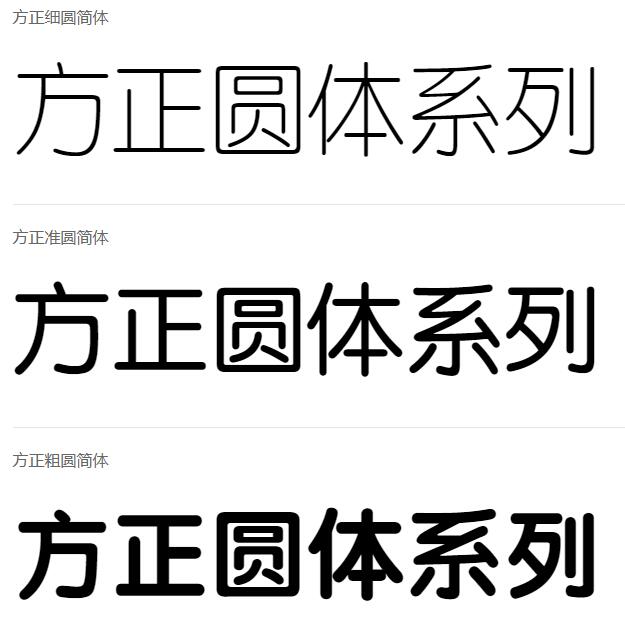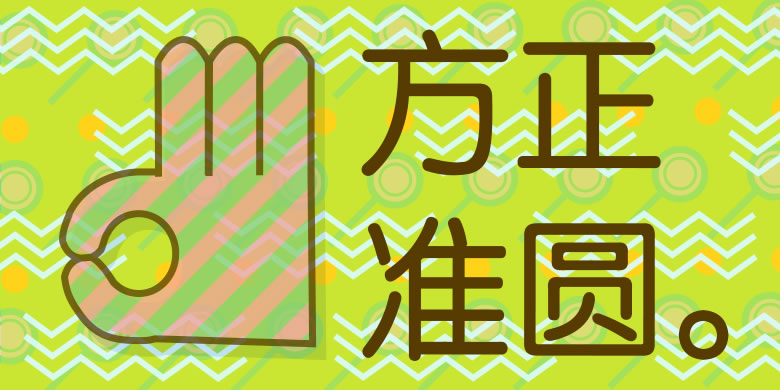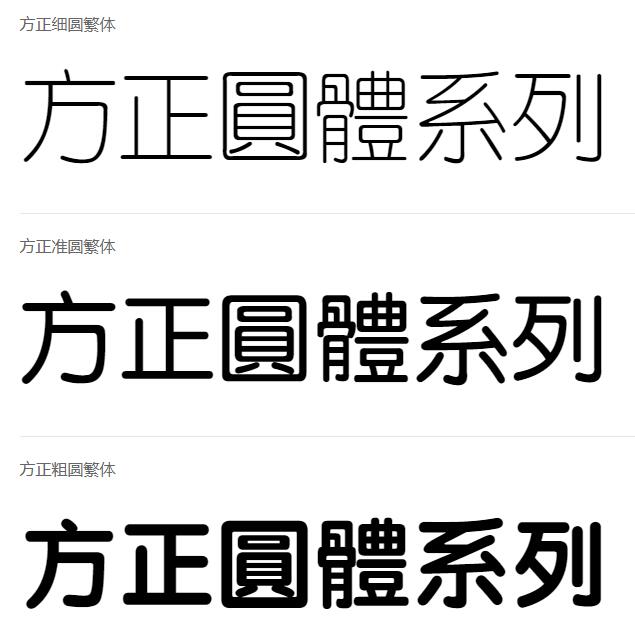
方正细圆繁体方正圆体系列
方正圆体家族的中宫宽松,字面大,起笔处与收笔处为圆形,折笔处呈圆弧状。方正圆体家族的字形风格舒展柔和,适用于女性、儿童和生活用品类的宣传册和包装设计等。方正圆体家族包括3款字重,其中方正粗圆笔画厚重饱满,适用于标题;方正准圆笔画粗细适中,适用于正文排版;方正细圆笔画纤柔,也适用于正文排版。